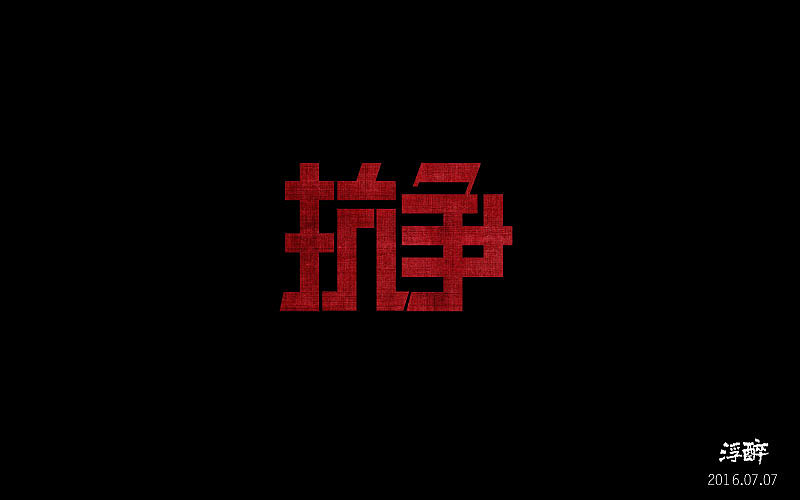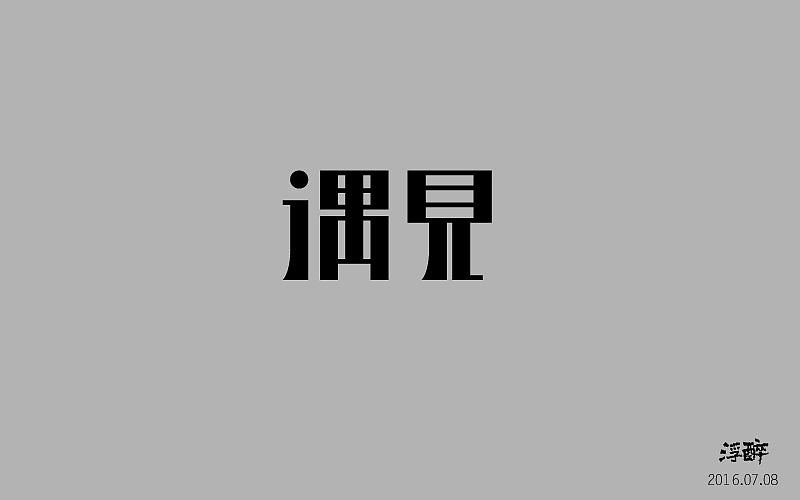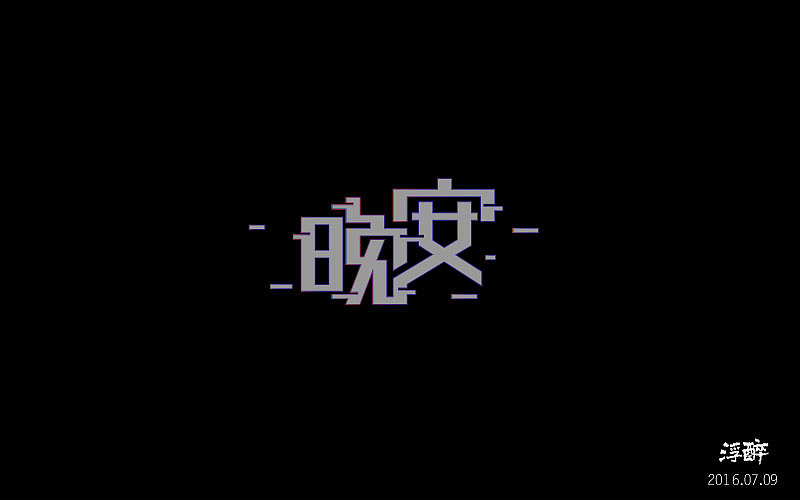
字体帮(四) 16.07.03-16.08.17
16.07.03 印象 (做完后,现在在看一看 的确还是很难看)
16.07.04 意外 (做完后再看,自己都感觉难看 .....)
16.07.05 北京
16.07.06 帮派
16.07.07 抗争
16.07.08 遇见
16.07.09 晚安
16.07.10 靠谱
16.07.12 纠结
16.08.17 过错